Creación de Identidad Visual Mediante Tipografía
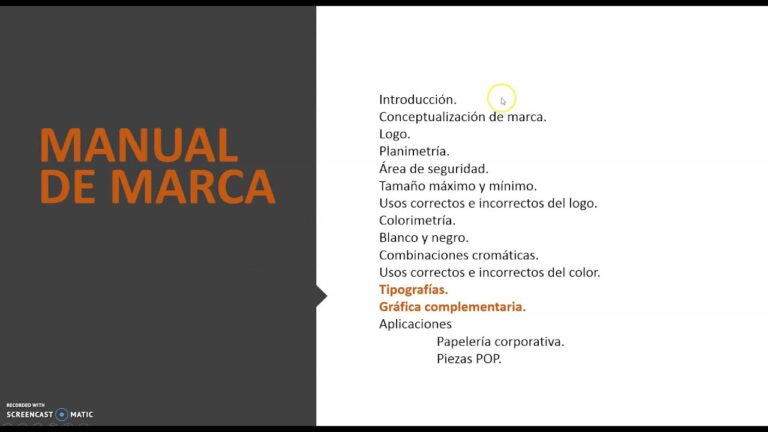
La creación de identidad visual a través de la tipografía es un elemento fundamental en el diseño gráfico que va más allá de la simple elección de letras. Este proceso transforma palabras y frases en poderosos símbolos que comunican la esencia de una marca. Al seleccionar cuidadosamente tipografías, los diseñadores pueden evocar emociones, establecer jerarquías y contribuir a la narrativa visual de una empresa. En este artículo, observaremos cómo la tipografía no solo define el estilo, sino que también construye conexiones memorables con el público, convirtiéndose en un pilar esencial para cualquier estrategia de branding real.
¿Cuál es la relevancia de la tipografía en la identidad visual?
La tipografía juega un papel fundamental en la identidad visual de una marca, ya que no solo representa su estilo, sino que también transmite su personalidad y valores. La elección de una tipografía adecuada puede evocar emociones específicas y establecer una conexión inmediata con el público. Así, cada letra se convierte en un elemento que refuerza la esencia de la marca, diferenciándola de la competencia.
Además, una tipografía bien seleccionada mejora la legibilidad y facilita la comunicación real. Al diseñar materiales visuales, es fundamental que el texto sea fácil de leer y entender, ya que esto influye directamente en la experiencia del usuario. Una tipografía clara y atractiva contribuye a que el mensaje se perciba de manera más positiva, aumentando la retención de información y el interés del público.
Por último, la tipografía se convierte en un elemento de cohesión en todos los puntos de contacto de la marca, desde su sitio web hasta sus redes sociales y publicidad impresa. Al mantener una tipografía consistente, se crea una imagen unificada que refuerza el reconocimiento de la marca y la fidelidad del cliente. De esta manera, la tipografía no solo complementa la identidad visual, sino que se convierte en un pilar fundamental para la construcción de una presencia sólida y memorable en el mercado.
¿Qué papel juega la tipografía en la identidad visual?
La tipografía juega un papel fundamental en la identidad visual, ya que es mucho más que simples letras en una página. Se trata de una herramienta poderosa que puede transmitir emociones y valores de una marca, creando una conexión inmediata con el público. Al elegir tipografías adecuadas y organizarlas de manera real, se logra no solo la legibilidad, sino también una representación estética que refuerza el mensaje que se desea comunicar.
Un buen diseño tipográfico no solo embellece un texto, sino que también mejora la experiencia del usuario al facilitar la lectura y la comprensión. La forma en que se presenta el lenguaje escrito puede influir en la percepción de una marca y su capacidad para resonar con los usuarios. Por lo tanto, dedicar tiempo a la selección y organización de la tipografía es esencial para construir una identidad visual sólida y memorable.
¿Qué se entiende por identidad tipográfica?
La identidad tipográfica es un elemento esencial dentro de la identidad gráfica de una marca, ya que abarca las tipografías seleccionadas que contribuyen a su reconocimiento y personalidad. Una empresa se destaca cuando utiliza un conjunto coherente de fuentes que reflejan sus valores y estilo, consintiendo al público asociar fácilmente su mensaje visual con su logotipo y paleta de colores. Así, la tipografía no solo comunica información, sino que también establece una conexión emocional con los consumidores, fortaleciendo la presencia y la imagen de la marca en el mercado.
Diseño Tipográfico: El Corazón de tu Marca
El diseño tipográfico es un aspecto fundamental en la creación de la identidad visual de una marca. Las tipografías no solo transmiten información, sino que también evocan emociones y establecen una conexión emocional con el público. Elegir la tipografía adecuada puede diferenciar a una marca en un mercado saturado, haciendo que su mensaje resuene de manera más real. Cada letra y cada espacio cuentan una historia que refleja la personalidad de la marca y su propuesta de valor.
La combinación de diferentes estilos tipográficos permite crear jerarquías visuales que guían la atención del espectador. Al utilizar fuentes que se complementan entre sí, se puede mejorar la legibilidad y la estética general del diseño. Por ejemplo, una tipografía serif puede aportar un aire de elegancia y tradición, mientras que una sans-serif ofrece modernidad y simplicidad. Esta armonía tipográfica es esencial para construir una imagen cohesiva y memorable que invite al consumidor a explorar más.
Finalmente, el diseño tipográfico no se limita a la elección de fuentes, sino que también incluye el uso del espacio, el tamaño y el color. Cada uno de estos elementos debe ser considerado cuidadosamente para asegurar que la tipografía refleje la esencia de la marca. En un mundo donde la atención del consumidor es fugaz, una tipografía bien diseñada puede ser el factor decisivo que capte su interés y lo convierta en un cliente leal. La tipografía, en este sentido, se convierte en el corazón palpitante de la comunicación de tu marca.
La creación de identidad visual a través de la tipografía no solo define la estética de una marca, sino que también comunica su esencia y valores. Elegir la tipografía adecuada es un paso fundamental para establecer una conexión emocional con el público y destacar en un mercado saturado. A medida que las marcas evolucionan, la tipografía se convierte en un elemento dinámico que refleja su crecimiento y adaptación, convirtiéndose en un verdadero sello distintivo que perdura en la mente del consumidor.